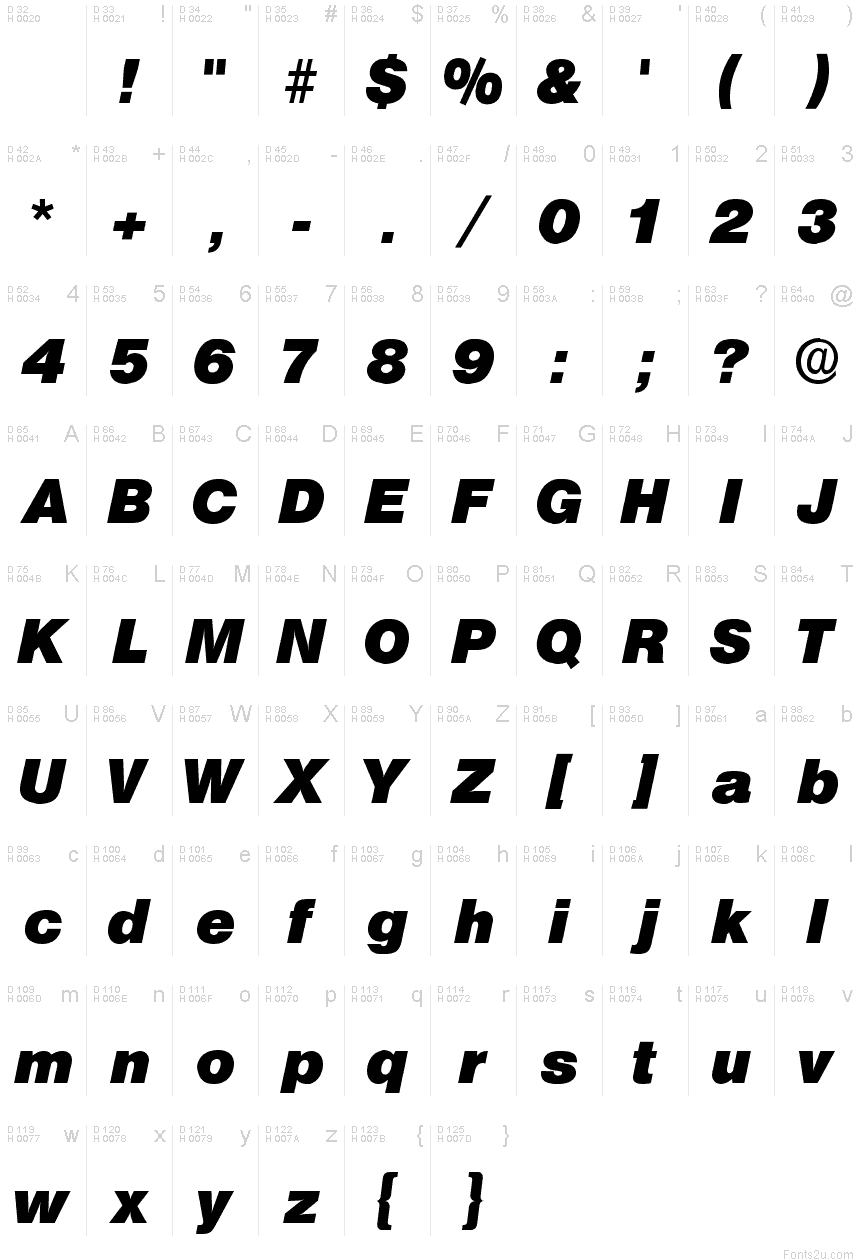
N.O.- Technique (ChoqueDisplaySSiBoldItalic)
N.O. Technique von Southern Software ist eine kostenlose, kursive serifenlose Schrift mit der harten Techno-Attitüde der 90er Jahre. Die Buchstaben drängen in einer kompakten Bewegung nach vorne, mit schweren, stumpfen Formen und engen, fast industriellen Kurven, die diese Schrift für Bewegung statt für Eleganz gemacht wirken lassen.
Sie passt perfekt auf Club-Flyer, Spielverpackungen, Sportgrafiken, Poster-Überschriften und Titelkarten, wo ein kostenloses Font-Design einen schnellen, aggressiven Kick braucht. Nutze sie für kurze Branding-Elemente oder Cover-Texte, wenn du willst, dass der schräge, kraftvolle Look die Arbeit für dich erledigt – denn diese Schrift liefert Geschwindigkeit und Wirkung, noch bevor du etwas anderes hinzufügst.